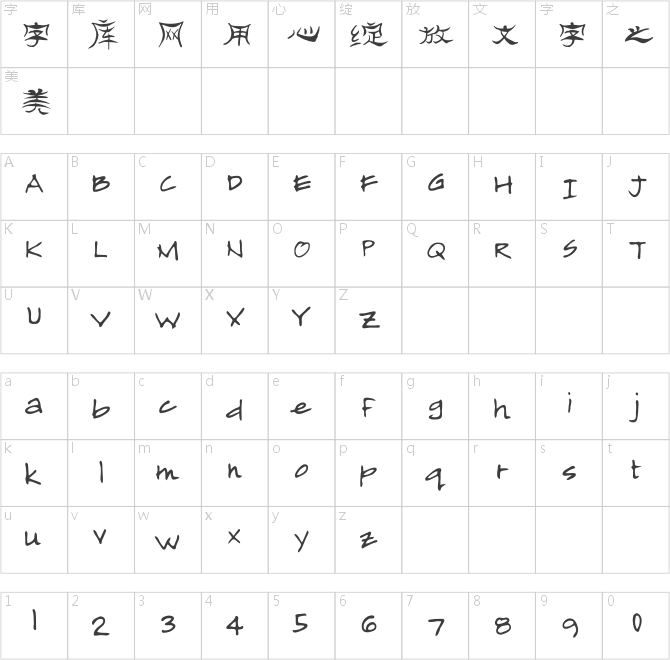
字體名稱: 天蠶字庫
天蠶書法在書法史上起著承前啟后的作用,具有歷史性突破。秉承歷史的印跡,運筆多變,體態(tài)萬千,如天蠶游戲紙間。厚重中透著靈活,整體結構變幻靈動,自帶風云。字里行間有一種陰陽互動的神韻,仿如羅漢坐禪,又如八卦神轉,字與字間透漏著中華民族獨有的文化和神韻。天蠶書法重新問世,為中國的傳統(tǒng)文化又添了濃重的一筆。天蠶書法區(qū)別于傳統(tǒng)隸書的蠶頭燕尾,以禪入書講述外能離相,內不著相。運用放大“橫”畫的中間力量來彰顯蠶一生蛻變的艱辛,天蠶書法對字體的筆畫,間架結構進行了大膽的創(chuàng)變,使其形式逐步走向單純與自然,回歸到漢字藝術自然書寫的本真。整體字形中規(guī)中矩彰顯得更方正,凸顯“橫”畫,用豎細畫調節(jié)整個字體的變化,形成臥蠶天趣。